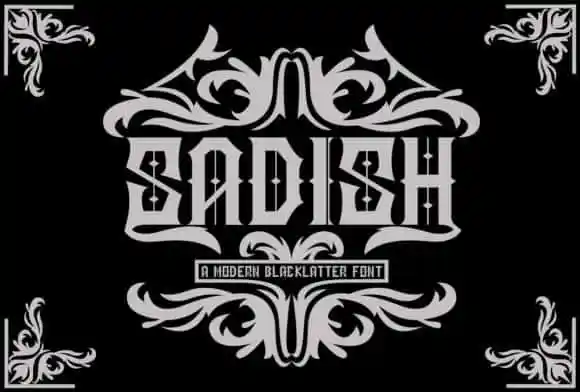
Sadish Blackletter Font – Download Grátis
A Sadish Blackletter Font é uma elegante tipografia moderna com contornos afiados. Inspirada na linguagem grafica do século XVII, a letra destaca-se como perfeita para aplicações que valorizam um estilo vintage e sofisticado. Este font foi criado pelo designer Sealoung no formato de fontes curvas, uma categoria que combina com os traços fluidos e elegantes da Sadish. Ideal tanto para aplicar em rótulos de bebidas alcoólicas, como na criação de logotipos retro ou identidades luxuosas, a Sadish traz um toque único de modernidade. Suas formas arredondadas proporcionam uma textura suave e vibrante, tornando-a perfeita para projetos que requerem um grau maior de personalização. A partir daqui, o uso do font é extenso e poderoso. Ele é especialmente adequado para criações de logotipos, identidades corporativas, designs de tatuagens e escrita em geral. Em sua natureza curvada e modernizada, a Sadish Blackletter Font transforma qualquer projeto num design impressionante. Obrigado à designer Sealoung pela criatividade desta fonte excepcional, agora disponível para quem busca uma mistura de antiguidade com modernidade na sua próxima criação gráfica.